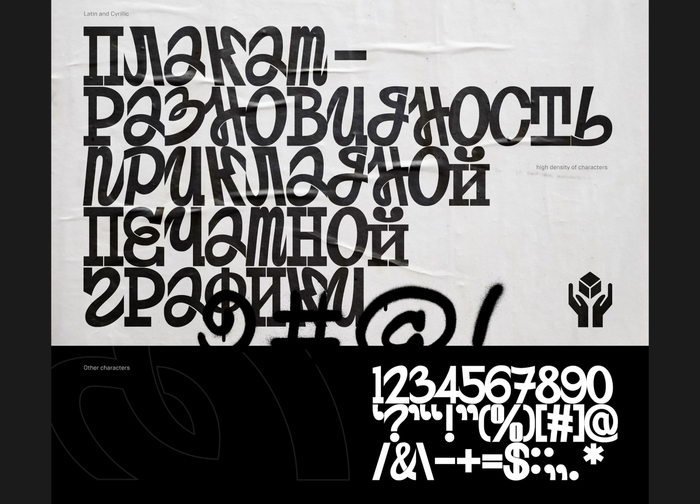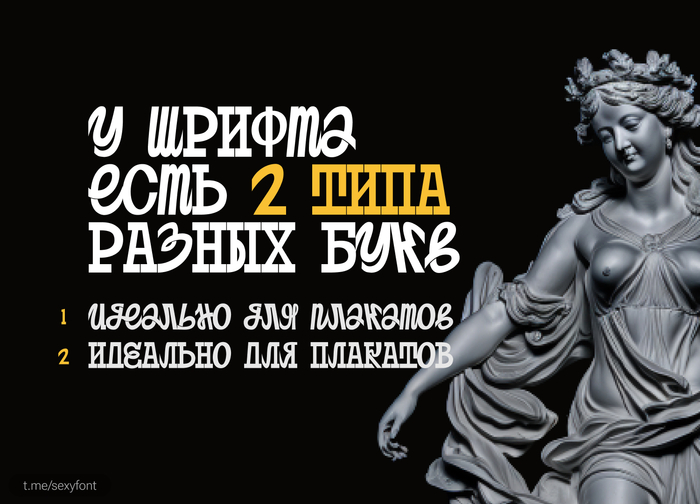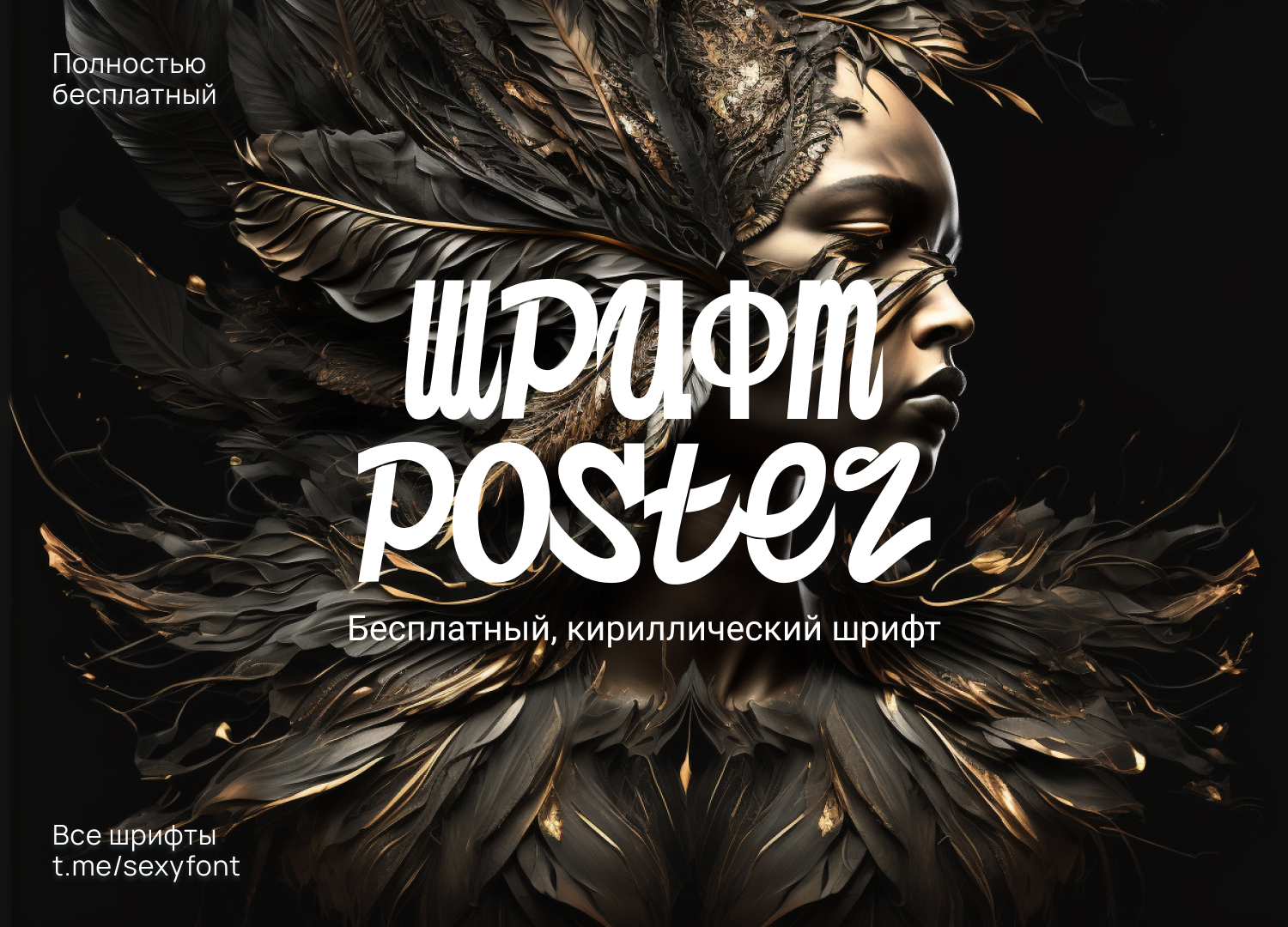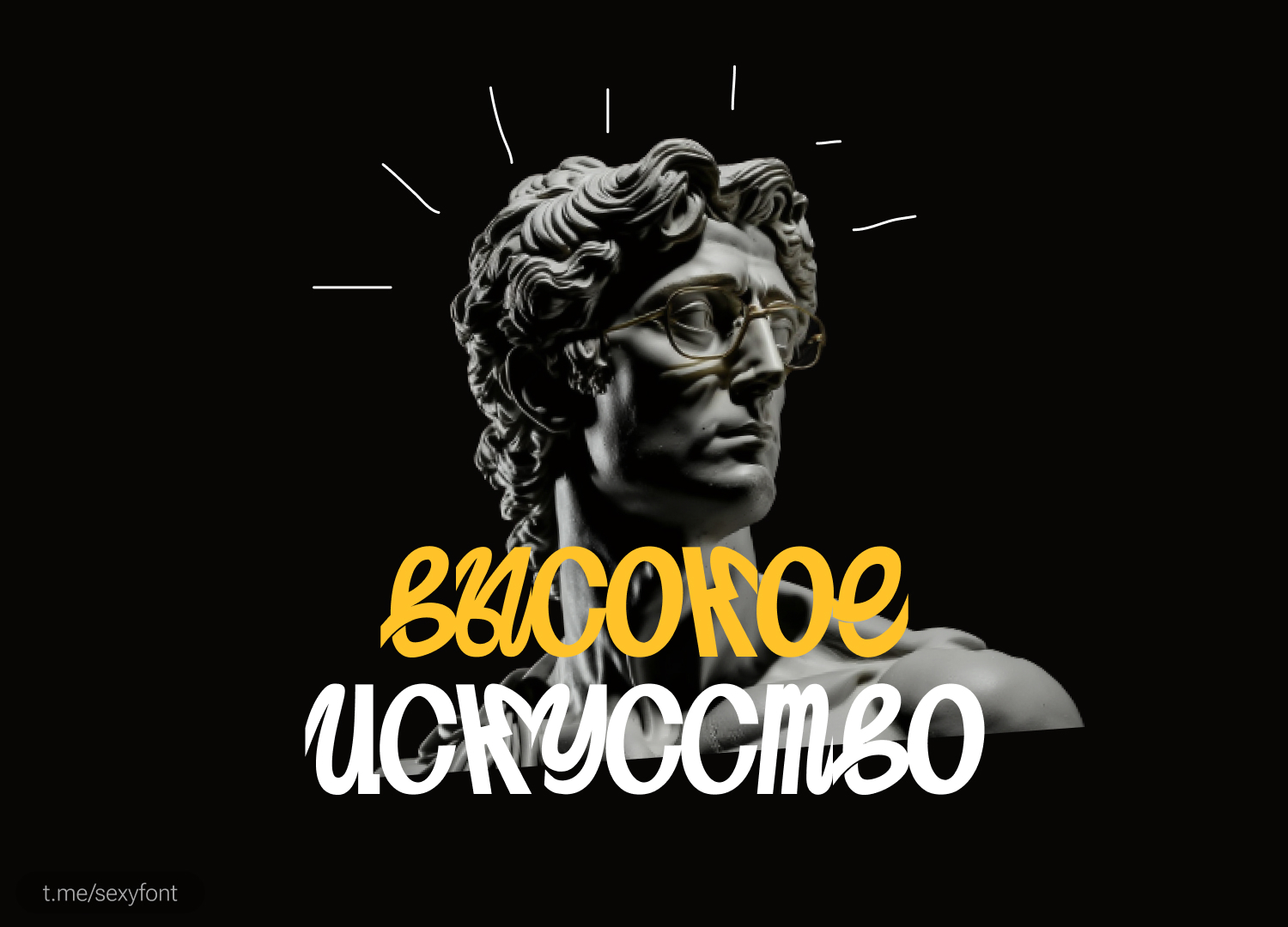
Шрифт постер. Кириллица
Постерный шрифт. Акцидентный, поэтому читаемость не шик. Для коротких словечек самое оно. Но буквы выглядят очень необычно. По лицензии, написано бесплатно. Конкретно для личного или коммерции автор не указал.